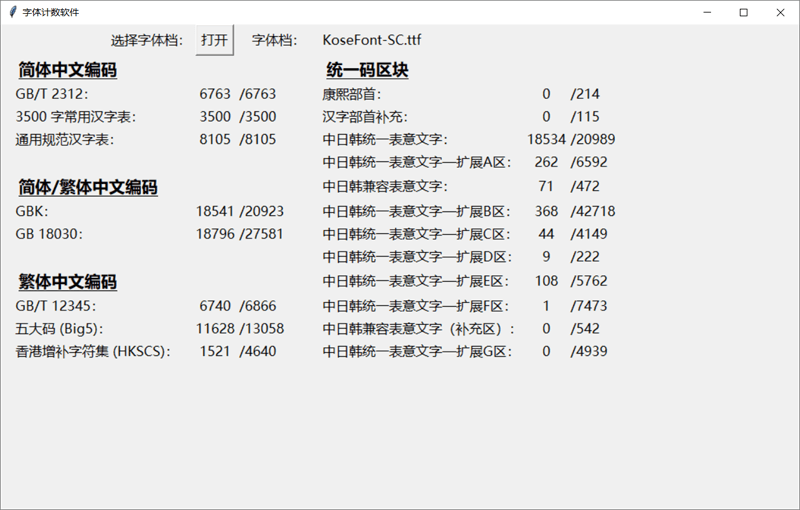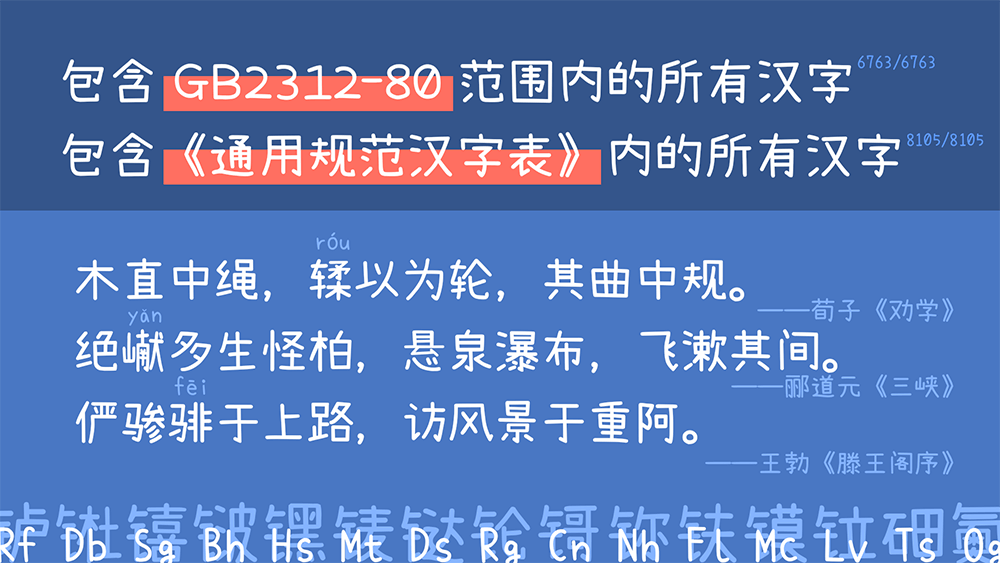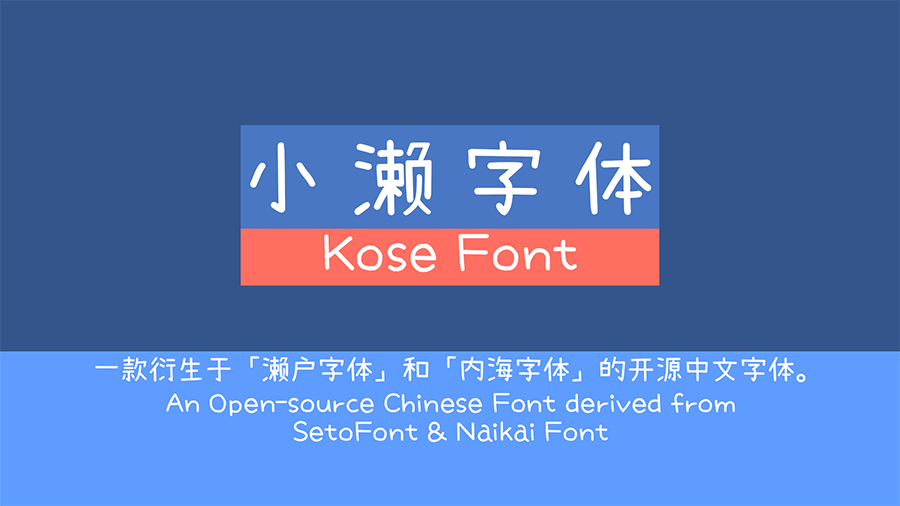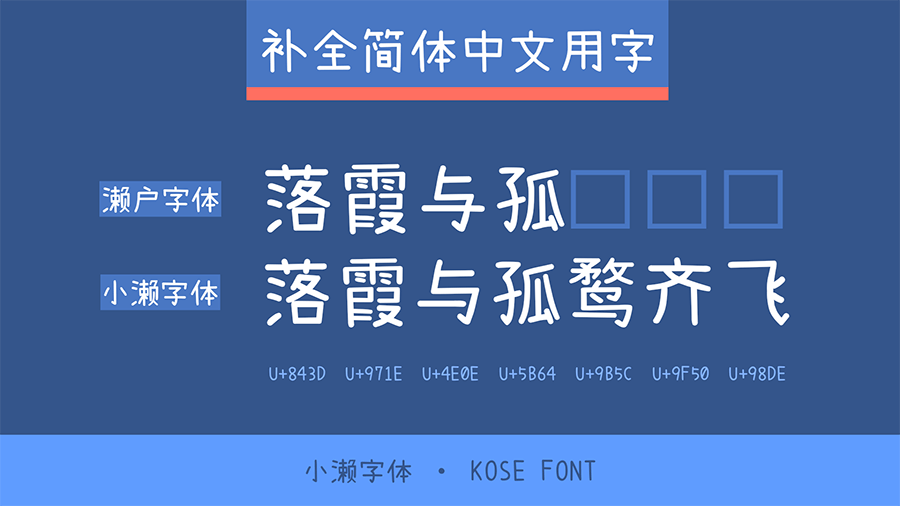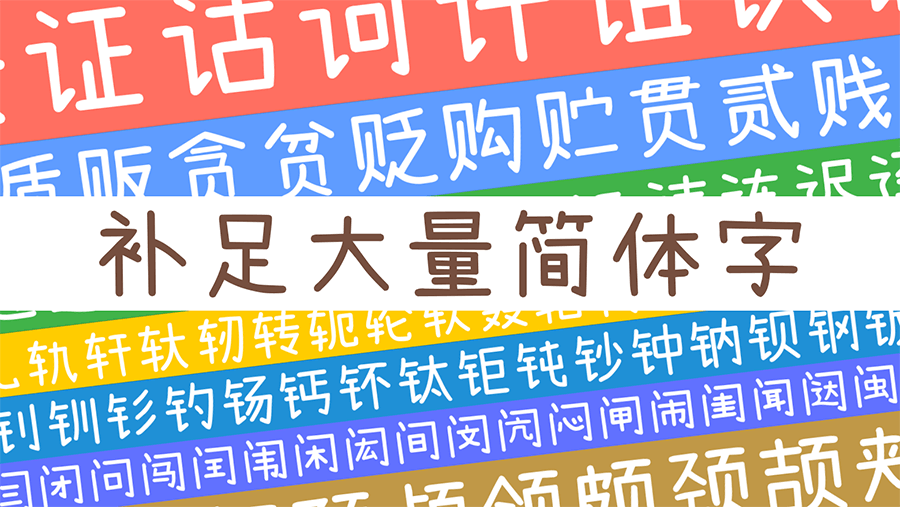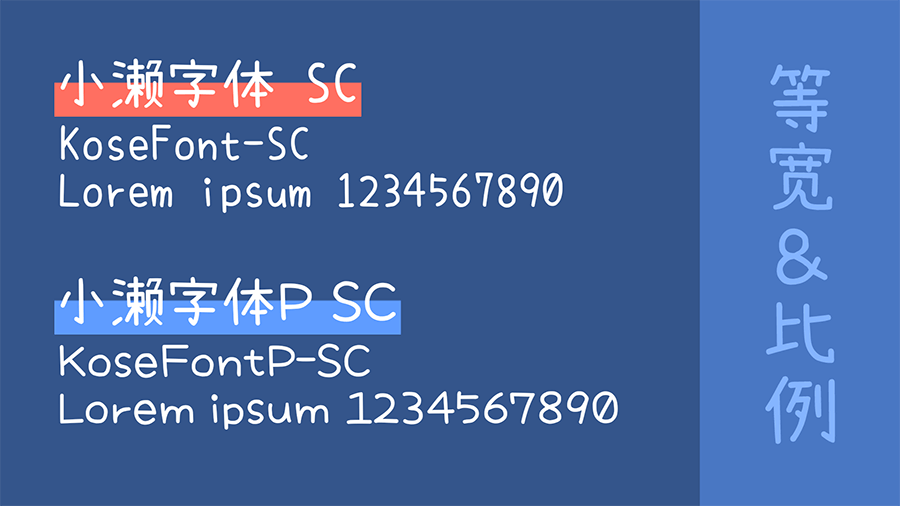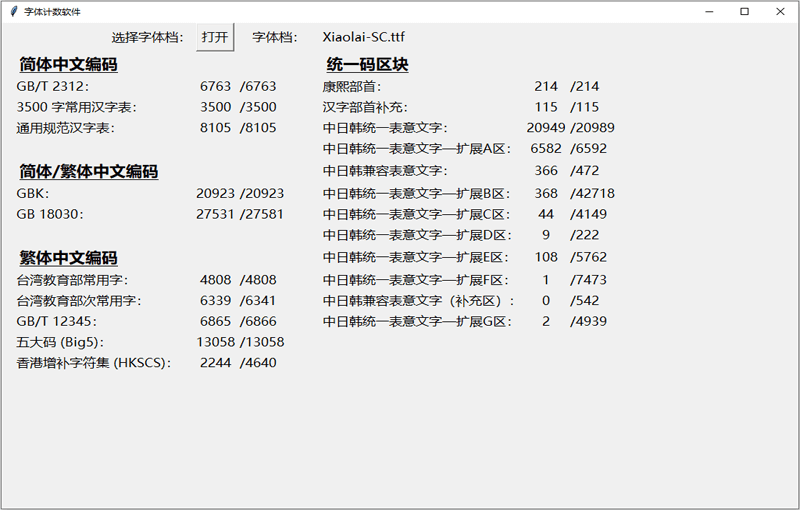
小赖字体:基于濑户内海字体补全简体 免费商用手写字体
字体作者:落霞孤鹜 (中国大陆) 字体字重:1个
本字体原名小濑字体,现在正式命名为“小赖字体”。
濑户字体是由日本的业余字体设计师瀬戸のぞみ制作,支持JIS第一至第四级,支持繁体和简体中文(部分)。目前最新的版本是2014年9月24日的6.20版本,原作者已经很久不更新了。
这款可爱的开源字体,仍然缺少一部分简体字,这对于大陆的用户来说,可能会造成一些不便。在这样的背景下,国内设计师“落霞孤鹜”开始了这个项目,旨在补足濑户字体缺少的简体字。落霞孤鹜利用业余时间将濑户字体原有的部件进行拼接和调整,补全简体中文汉字。
后来本站网友“猫啃新人” 发现“落霞孤鹜”的版本在竖排的时候会出现文字粘连的问题,于是对字体进行了修正,并把修正后的字体命名为“濑户字体简体”,并把字体的宽度由2024调整为1000,修正了原来版本在竖排文字的时候出现的文字粘连问题。精简了大量用不上的其它国家和地区的字符。
于2020年05月16日, 设计师落霞孤鹜在猫啃新人修正后的版本基础上,继续对此字体进修优化,并正式把字体的名称命名为“小濑字体”。
于2020年05月17日,猫啃新人继续对新版本的“小濑字体”进行优化,增加了一些OpenType功能。 在使用ps等支持Opentype功能的软件对文字进行竖排显示时,一些标点的显示会更合理。而且由于新添加了一些日本漫画常会用到的特殊符号如连续波浪线或斜叹号等,若有日漫汉化组使用该字体的话,嵌字会更加方便。如需查看修改了哪些地方,可以查看本文底部的版本更新纪录查看。
于2020年06月19日,字体作者落霞孤鹜把字体更名为“小赖字体”,是因为很多朋友搜索的时候会把“濑”字打成“赖”。现在这款字体依然在持续维护更新中。
项目简介
濑户字体 是由日本的业余字体设计师 瀬戸のぞみ 制作,支持 JIS 第一至第四级,支持繁体和简体中文(部分)。目前最新的版本是 2014 年 9 月 24 日的 6.20 版本,原作者已经很久不更新了。
后来,Max 在原来的「濑户字体」基础上,推出了 内海字体 ,补齐了台湾教育部门列出的 4808 个常用字,并增加了闽南语、粤语常用字,弥补了繁体中文地区常用字缺字缺憾。
但是,这款可爱的开源字体,仍然缺少一部分简体字,这对于大陆的用户来说,可能会造成一些不便。
于是,本人开启了 “濑户内海字体简体补全计划” ,旨在补足 濑户字体 缺少的简体字。 小赖字体 是这一计划的延续。
本字体项目原名为 「小濑字体」 ,后来由于很多人都把「濑」打成「赖」,索性把「氵」去掉,改名 「小赖字体」 。
字体概况
本字体是 濑户字体 的简体中文化改良,利用濑户字体里原有的部件,对原字体中缺少的汉字进行补足,主要为 GB2312 及《通用规范汉字表》里的汉字,其余的汉字、谚文、特殊符号用 cjkFonts 全濑体 补全。现有 CJK 基本区汉字 20949 个,扩展 A 区汉字 6582 个,B 区汉字 368 个,C 区汉字 44 个,D 区汉字 9 个,E 区汉字 108 个,F 区汉字 1 个(「韡」的简体字「?(U+2E9F5)」),G 区汉字 2 个(biáng 字的简繁体「?」(U+30EDD)「?」(U+30EDE))。
该字体可显示 GB18030-2000 范围内的全部汉字(共 27484 个),以及《通用规范汉字表》里的全部汉字(共 8105 个),满足中国大陆用户的使用需要。此外可显示日文假名、谚文 (韩文、朝鲜文) 音节和思源黑体可以显示的特殊符号,可直接用作手机字体。
此外新增日本写法的字体,保留「濑户字体」原汁原味的日系风格。日本版保留原 「小濑字体(Kosefont-JP)」 名称。
注意事项
1、本字体可以显示所有 GB 2312 及“通用规范汉字表”里的所有汉字,不过制作时间比较仓促,不保证里面所有的字形都是中国大陆的规范字形,欢迎大家通过 Issues 反馈。
2、本人并不是专业的设计师,并未考虑设计美感,所以看起来可能略丑,补进去的字与原版可能略有违和感,但是聊胜于无。
3、本字体已经删去了原字体除中文、西文、日文、希俄以外的多余的语言文字,包括韩文。
小濑字体也提供了两个版本可供下载,包括简体版和日本版。保留濑户字体原汁原味的日系风格。日本版保留原 「小濑字体(Kosefont-JP)」 名称。大家可以按自己的需求下载。这两个版本字体的差异请看下图。
字体应用